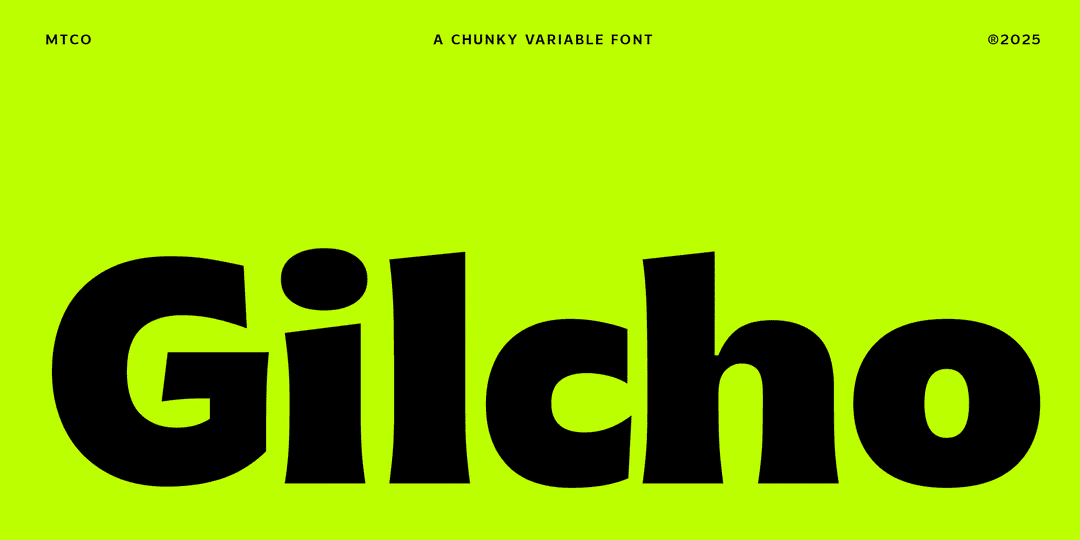
MTC Gilcho
読みやすいカジュアルなフレアセリフ。カウンターが大変大きめでxハイトも高くて可読性が良い書体で、フレアセリフながら雰囲気はややポップでカジュアル。グリフは700近くあって字種が豊富で、a や g はデフォルトでは2階建てだが、1階建てのオルタネートがある。g には1階建てにちょっと変わったグリフもまた別にある他、y は直線とフック状になった2種がある所がめずらしい。数字には白黒の丸数字もある。イタリックもあって9ウェイト。